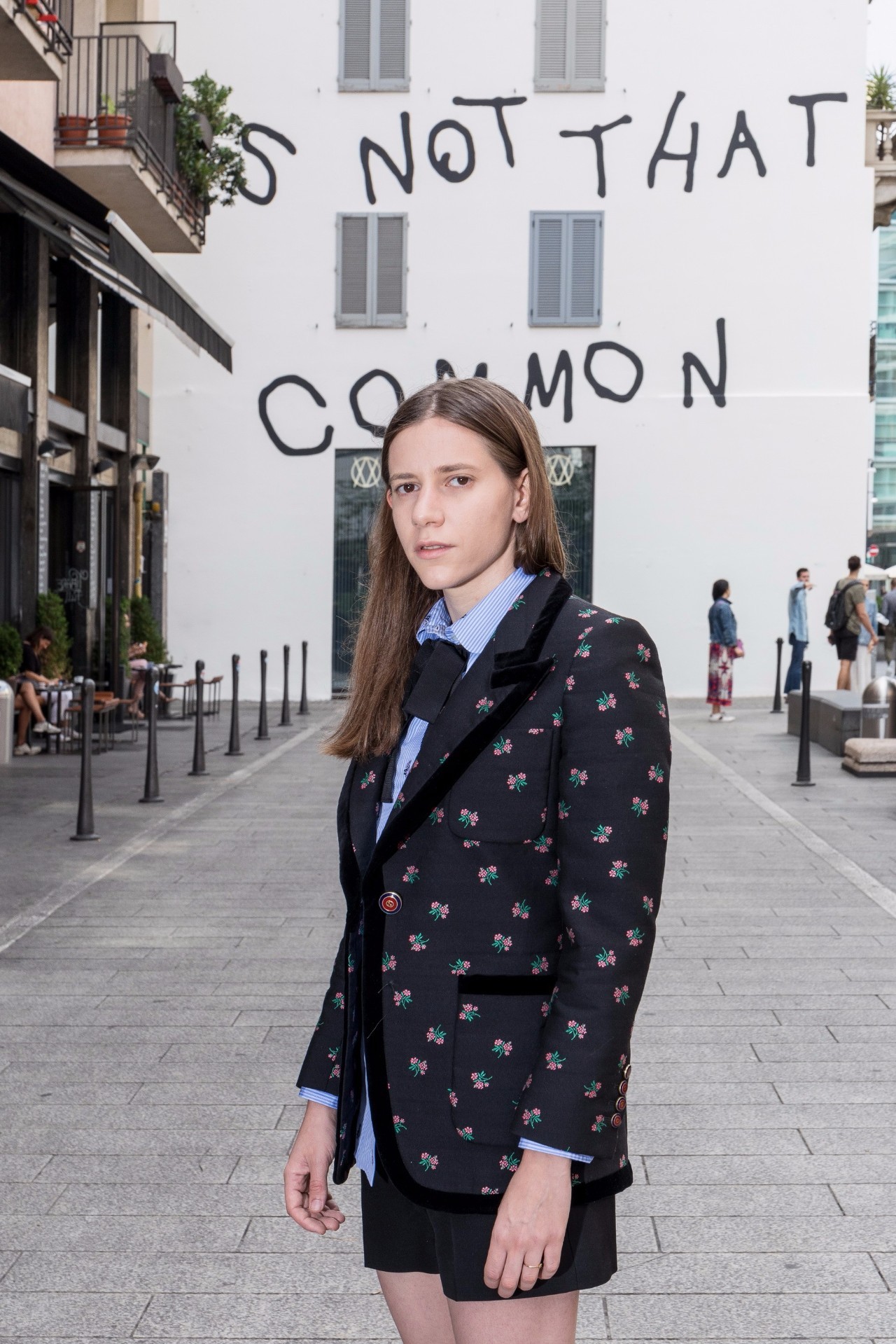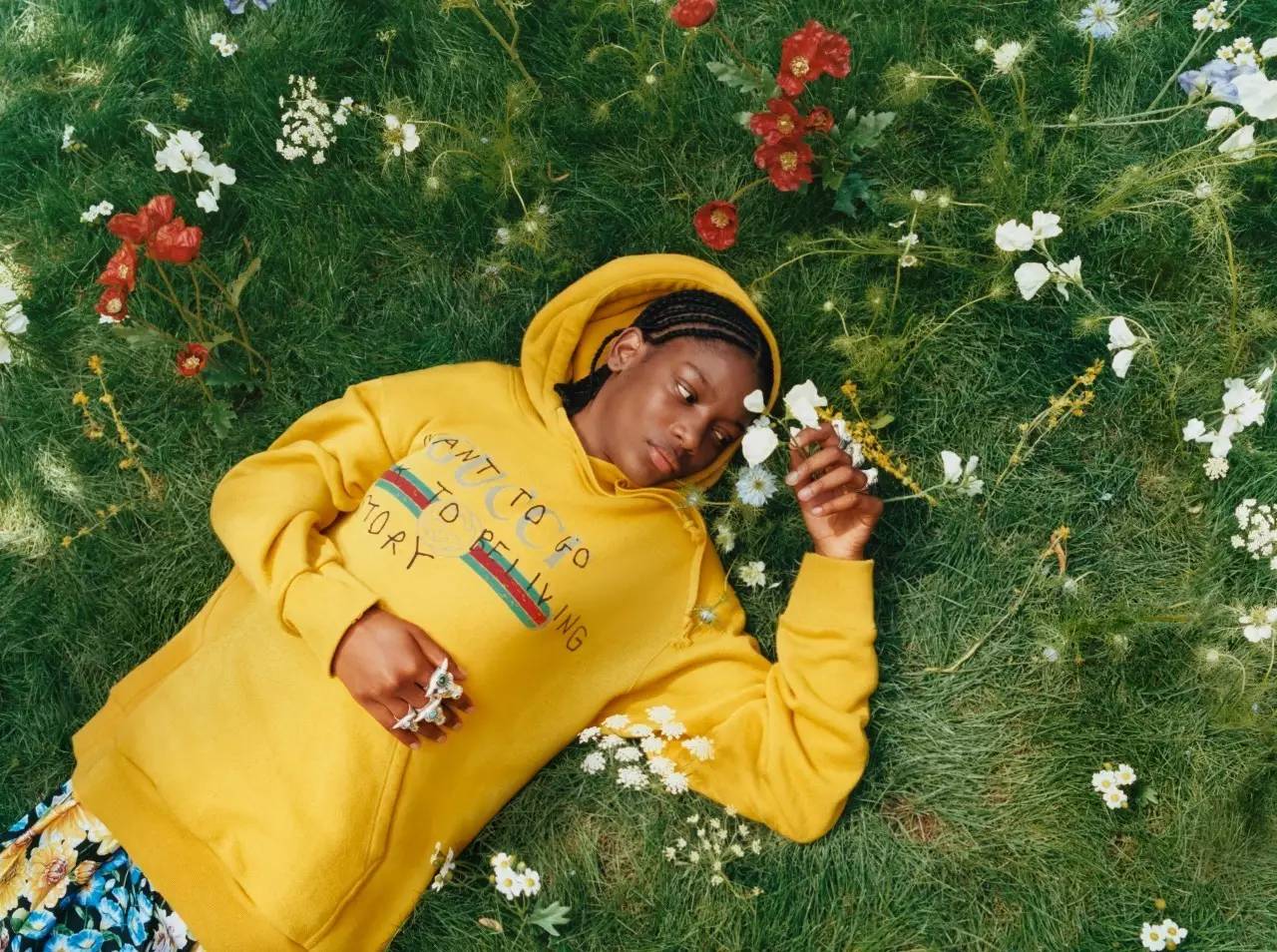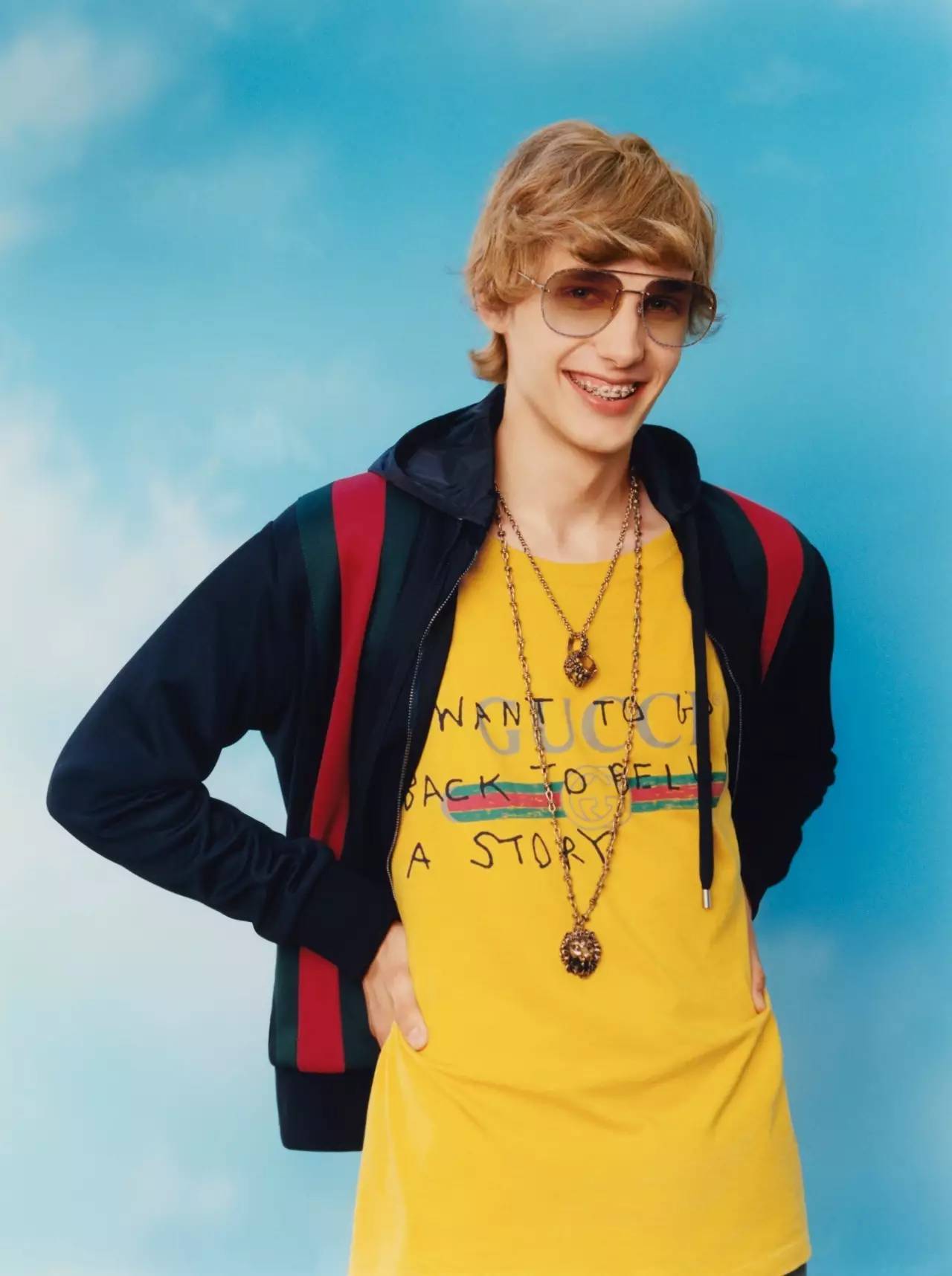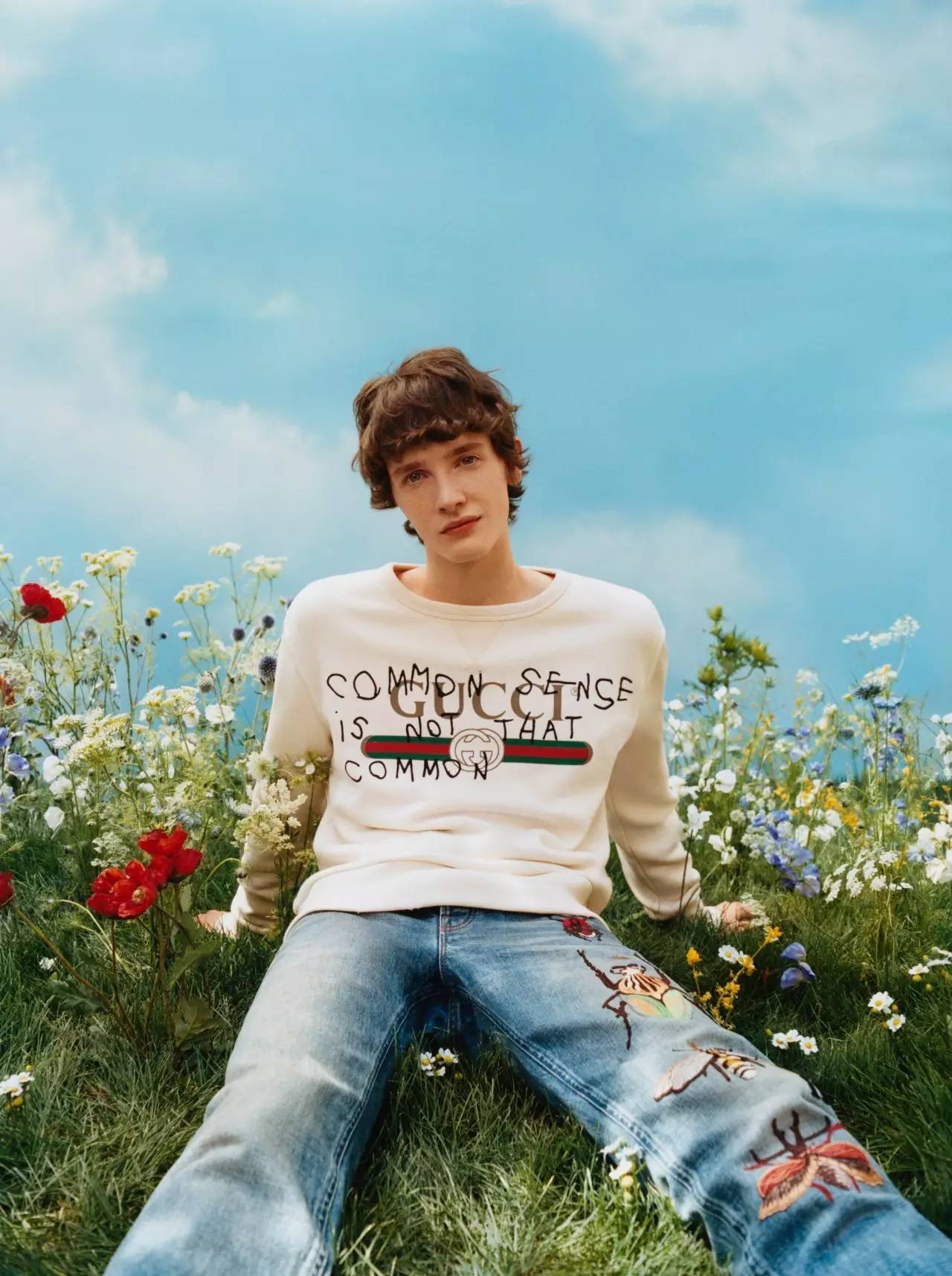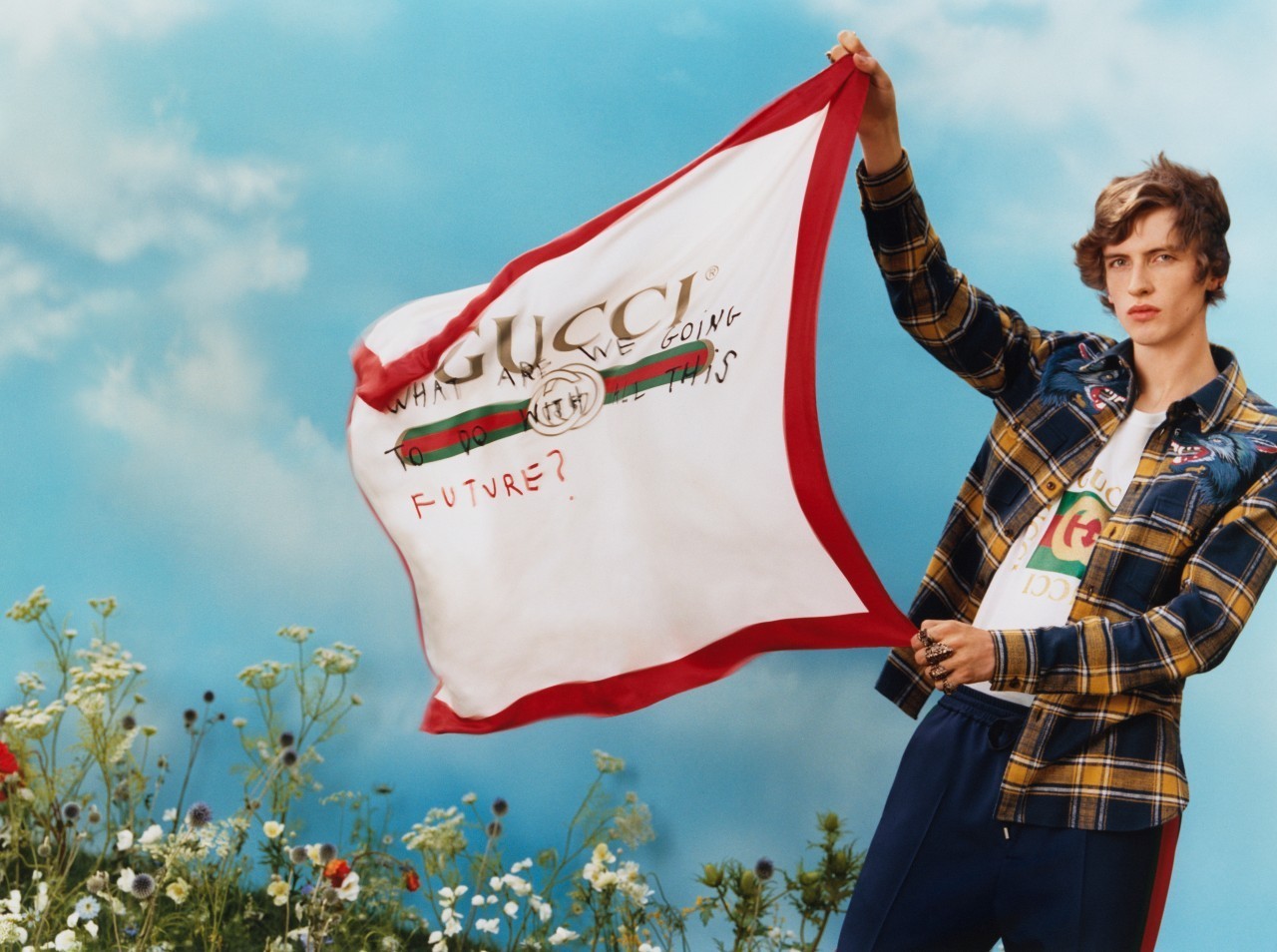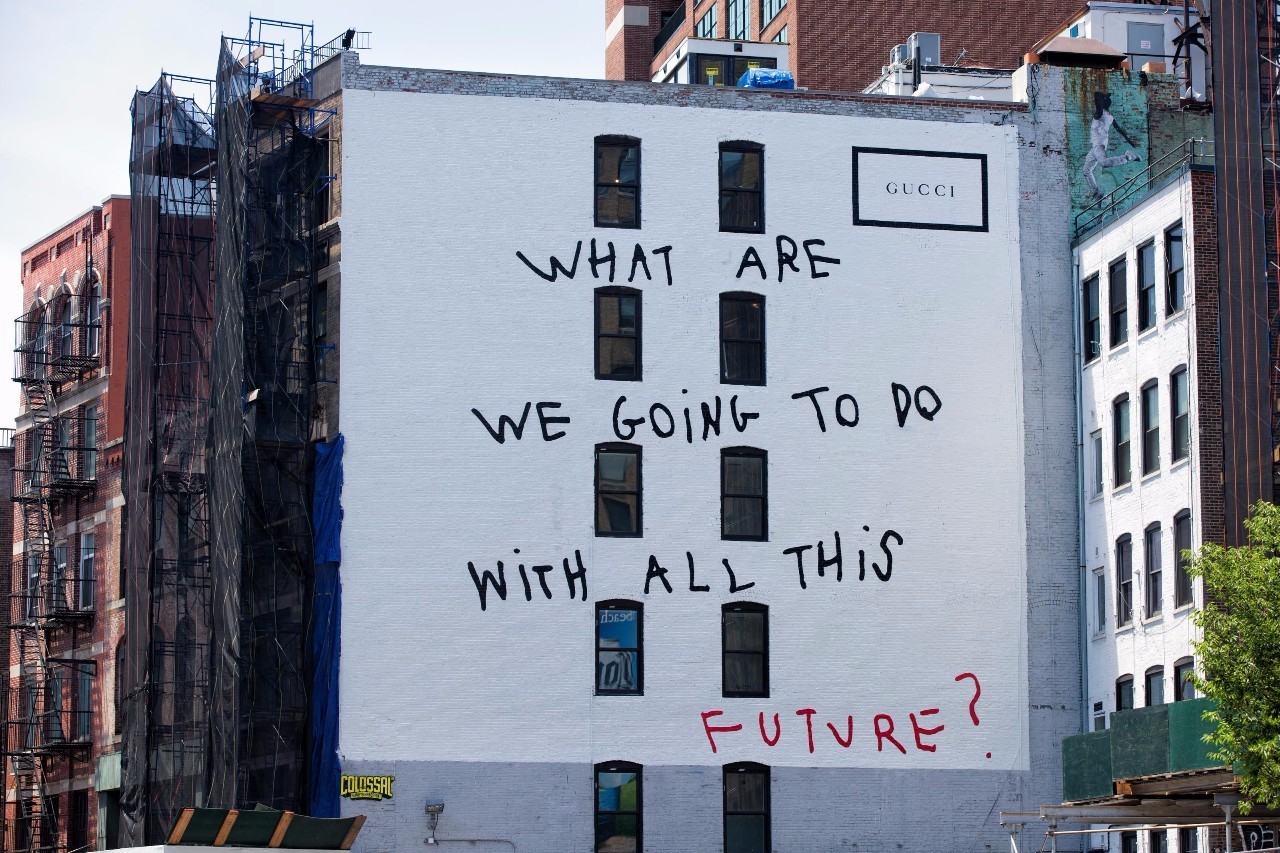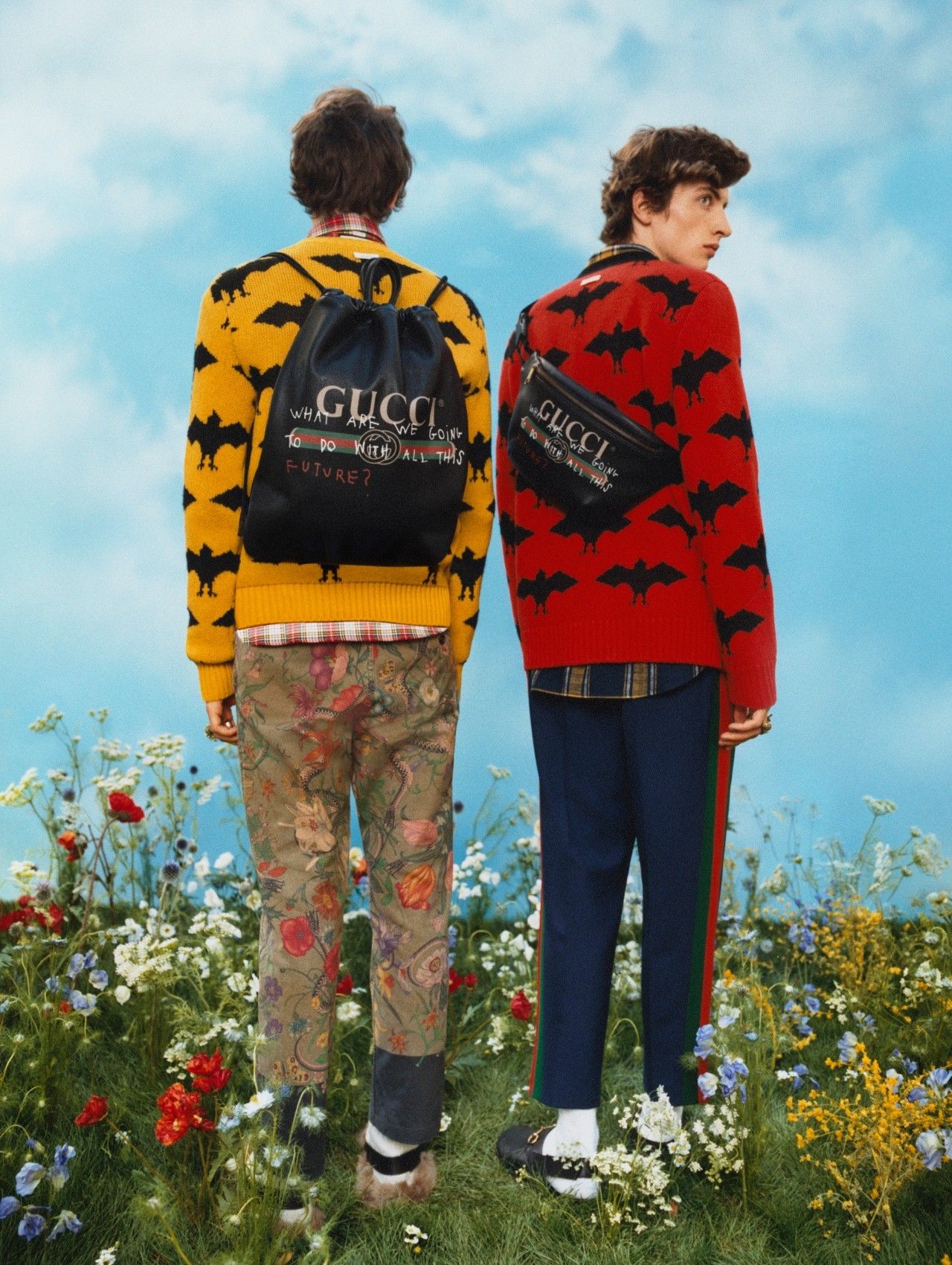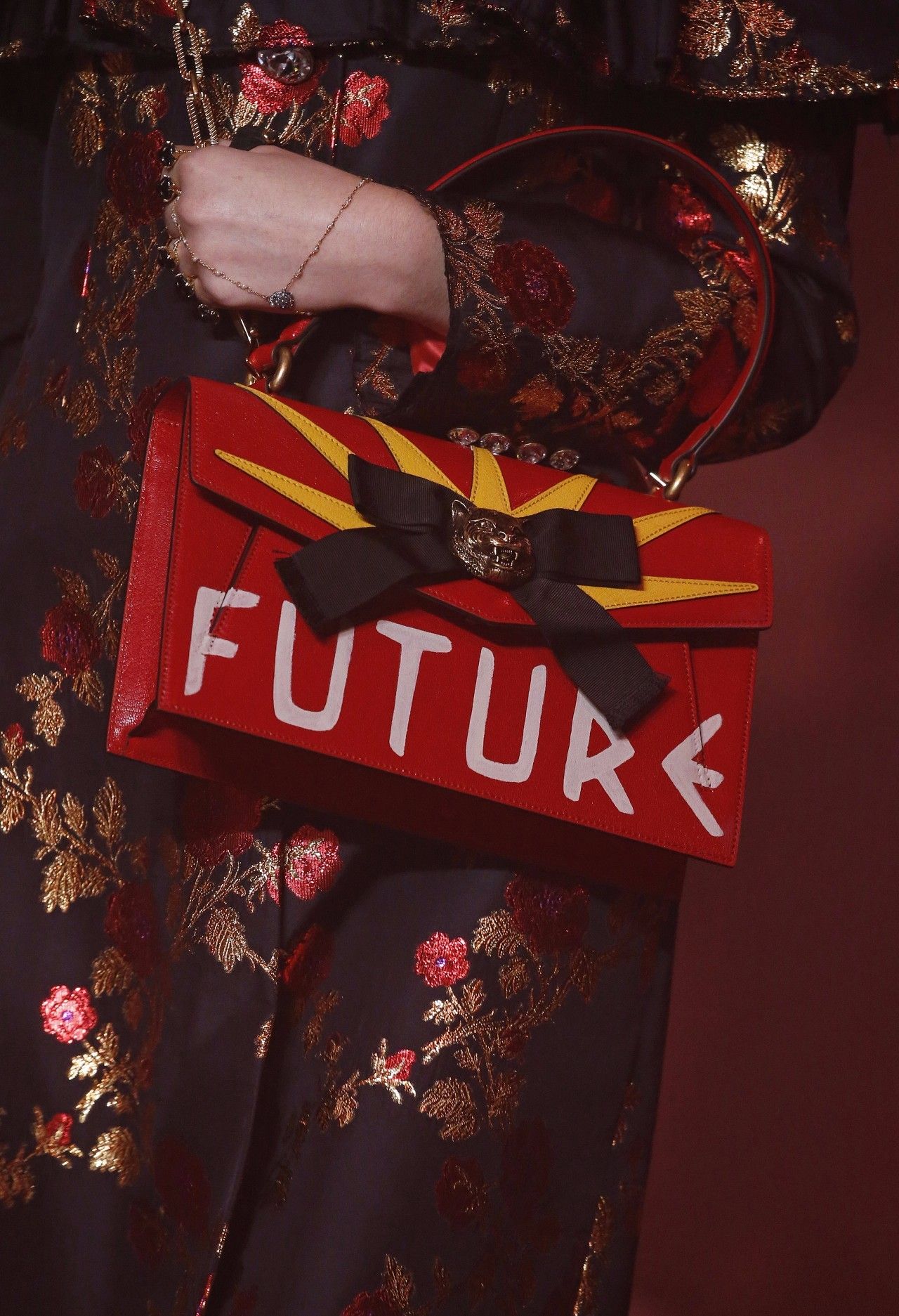
Gucci 我的文字态度
标语,一方面是意义的载体,是精神外化的呈现;另一方面它具有能被感知的客观形式。
如同罗兰·巴特 ( Roland Barthes ) 在《符号学基础》中所说,"任何一个符号都包括了能指/所指两个部分",分为表达层面和内容层面;如古埃及象形文字, 把过去保留在现在中, 过去在当下具有关键的意义; 如上世纪60年代位于伦敦的商店 Mr. Freedom 开始售卖带有标语的人物T恤。
穿在身上的"标语"就是鲜明直白的"自我"、"态度"或"诉求"。创作总监米开理藉由琳琅满目的专属美学符号,表达出最真实的自我风格。
穿梭时空的奇幻投影, 思维的神游畅想拥有更多天马行空的智趣遐思, 米开理借用充满未来感的设计语汇传递希望,期待未来梦想成真。
不同时代地域的文化似有万般魔力,摩登文化与人们追逐时尚潮流的意念不谋而合,衔接旧日寓意与新生特质成为品牌全新时髦印记。
我想回头去相信传说
出生于1992年的 Coco Capitán 来自西班牙,是一位画家兼摄影师。她的作品以简洁率真的时尚美学闻名,也在社交网络上表现活跃,发布内容以时尚、艺术、摄影及诗歌为主。
Coco Capitán:曾作为特邀艺术家参与"策展米开理"之北京篇章,运用书稿书写呈现其对意大利艺术绝对数量的沉思,及对科学和宗教的日记体随感。
她有着不同寻常的幽默感,她擅长讲述既天真又错综的故事,相信梦想的世界里不存在不美好的事物。
最新特别合作系列:呈现 Coco Capitán 极具标志性的存在主义风格书写手稿,诙谐戏谑的世界观与米开理不拘一格的浪漫主义情怀相融合。
常识其实也没那么寻常
Coco Capitán 这句充满哲学性的手写标语,更多的是表达对于日常生活,有很多事情是理所应当的,但并不是每个人的想法都一致。在辩证探究下所诞生的耳目一新,也再次强调米开理的自我表达主义。
对未来你想怎样?
Coco Capitán 对存在的发问,发人深省的标语,表达了她对人们所处的此时此刻的感思:没有人知道即将发生什么也没有人想要知道即将到来的事情。
品牌大使杰瑞德·莱托 ( Jared Leto ) 是米开理的好友,也是创意先锋。" Hollywood " 是他们一起出席好莱坞奥斯卡颁奖礼后所带来的影响,米开理将作为其创作灵感来源, 把 " Hollywood " 作为全新的精神标语。
米开理所信奉的浪漫主义思想" Blind For Love 执迷于爱"正源于18世纪法国女作家 Fanny de Beauharnais 的法文小说手稿" L'Aveugle Par Amour ( 执迷于爱 ) "。简洁的标语诠释米开理式的爱情哲学。
Blind For Love:爱情是盲目的,是精神的"痴迷",是人的灵魂对于"美"之本体的眷恋。文艺浪漫的设计语言成为描摹爱情最直接的方式。